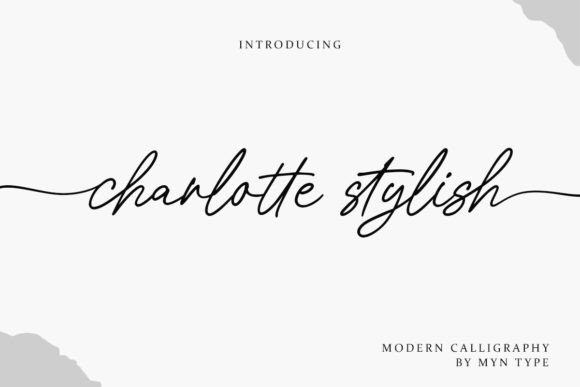
Charlotte Stylish
Charlotte Stylish – La Calligraphie Moderne qui Réinvente l’Art
Vous cherchez une touche d’originalité dans vos projets d’écriture ou de design ? Charlotte Stylish est la solution. Cette nouvelle approche de la calligraphie allie liberté créative et modernité, rompant avec les contraintes classiques tout en conservant l’élégance qui caractérise l’art de l’écriture.
- Créativité sans Barrières : chaque trait est une exploration, chaque lettre un nouveau défi.
- Liberté d’expression : laissez votre imagination prendre le dessus, sans suivre un modèle strict.
- Individualité Garantie : chaque œuvre est unique, reflétant votre personnalité.
- Adaptabilité : idéale pour invitations, logos, affiches ou travaux personnels.
Adoptez Charlotte Stylish pour donner à vos projets le caractère distinctif qu’ils méritent. Essayez-la dès aujourd’hui et transformez votre écriture en véritable œuvre d’art.